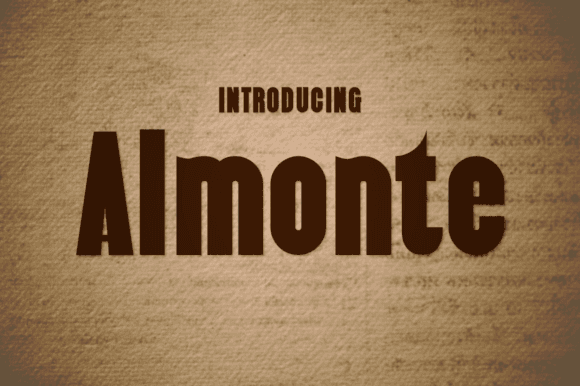
Fuente Almonte para manualidades, logotipos y proyectos de impresión
Almonte ofrece una estética dinámica y artesanal que se adapta a una amplia gama de aplicaciones creativas. Con líneas limpias y alta legibilidad, aporta una personalidad audaz a la artesanía, los logotipos y los medios impresos donde el impacto visual es clave.
Esta entidad fuente combina estilo creativo con utilidad profesional, brindando a los creadores, diseñadores y propietarios de negocios una herramienta flexible para amplificar el mensaje de la marca o agregar estilo a creaciones personalizadas.
Desde envases impresos hasta señalización de vinilo, Almonte está diseñado para funcionar allí donde las palabras necesitan presencia.
Lo que puedes hacer
- Etiquetas, pegatinas y señalización elaboradas
- Logotipos personalizados y recursos visuales de marca
- Tipografía de prendas de vestir y etiquetas de productos
- Carteles, tarjetas y folletos impresos
- Diseños de embalajes y entregables impresos
Por qué te encantará
- Letras audaces y expresivas para un texto destacado
- Ideal para manualidades, impresión y marca.
- Optimizado para mayor claridad tanto en medios digitales como físicos
P: ¿Qué tipo de fuente es Almonte?
A: Almonte es una fuente de visualización en negrita diseñada para manualidades, logotipos y medios impresos donde la fuerza visual es esencial.
P: ¿Es bueno para la impresión de alta resolución?
R: Sí, Almonte está optimizado para una impresión limpia y una fuerte visibilidad en los activos de diseño físicos.